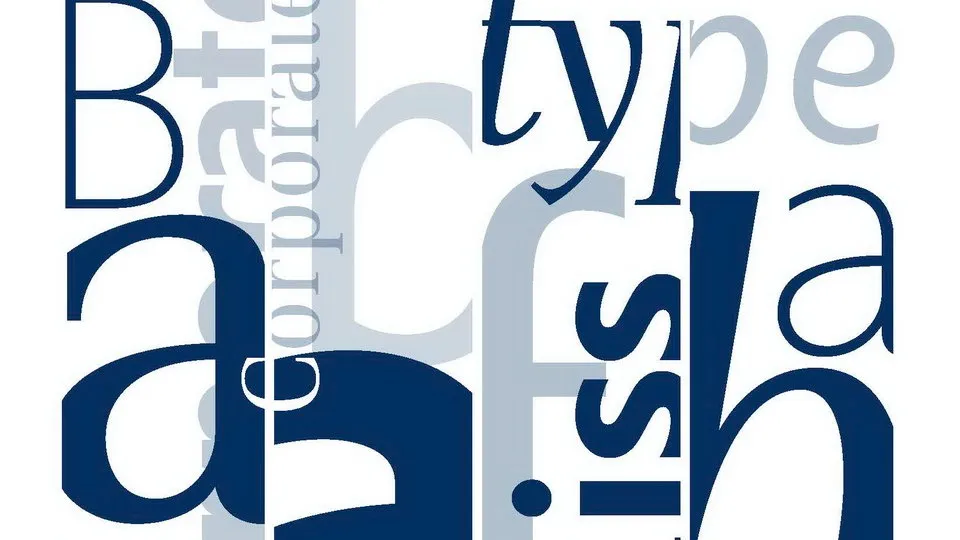
A fonte Luiss é uma combinação perfeita entre a elegância clássica dos serifos e o encanto vintage. Ela foi criada pelo talentoso Antonio Pace na 99designs, um marketplace de design que desperta paixão por criações únicas e impecáveis. Este projeto inovador e visionário busca transmitir valores como a inovação e liderança ao oferecer uma escolha única para representar a cultura corporativa com autenticidade. Cada detalhe da fonte Luiss é cuidadosamente criado pelo Luiss Type, que valoriza a independência operacional ao permitir que as empresas criem seu próprio estilo, sem ser influenciadas por padrões pre-existentes. O design de Luiss captura e transmite essas mensagens poderosas em cada caractere.